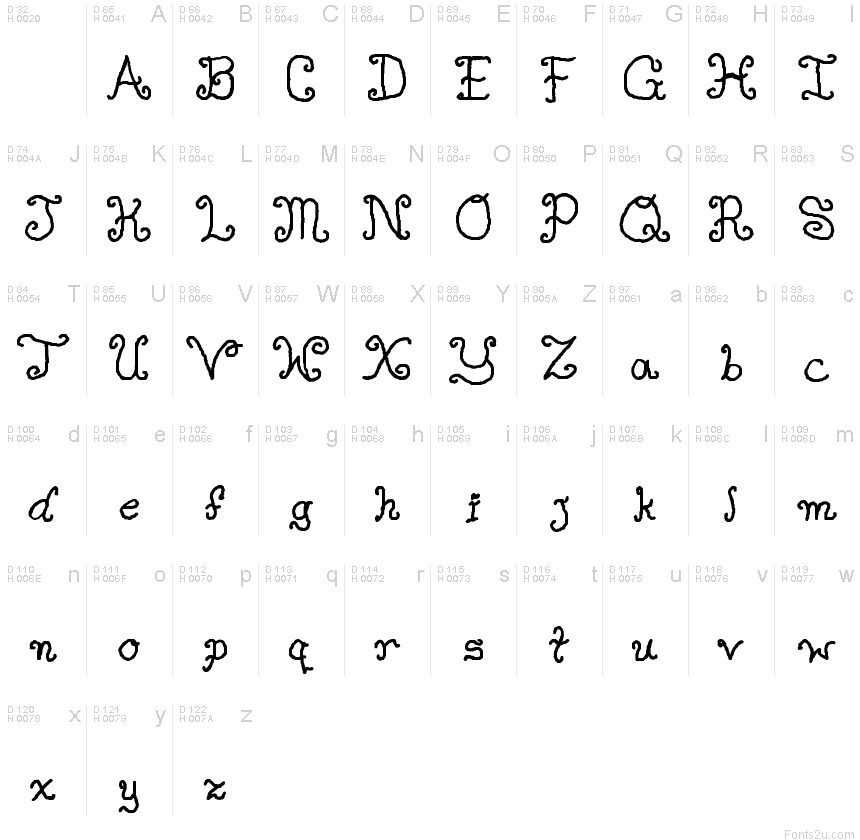
Single Gyrl autorstwa Heather Daniels to darmowy, fantazyjny krój odręczny z klimatem scrapbookingu z końca lat 90. Litery tańczą w zamierzenie nierównym rytmie, łącząc grubsze kreski z zawiniętymi końcówkami i małymi spiralami, co nadaje alfabetowi luźny, figlarny i nieco psotny charakter.
Idealnie sprawdza się w projektach wymagających osobistego, rękodzielniczego sznytu: okładkach zinów, opakowaniach w stylu pamiętnika, menu kawiarnianych, ulotkach imprezowych i krótkich nagłówkach, w których te zakręcone detale mogą grać główną rolę. Jako darmowy font, świetnie nadaje się też do kart tytułowych, cytatów czy monogramów, zwłaszcza gdy szukasz liter, które wyglądają na odręcznie narysowane, a nie na wygładzony, neutralny font typu script.